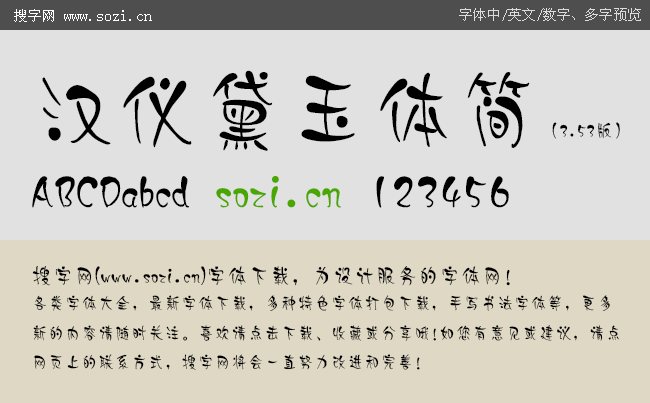
漢儀黛玉簡
搜字網(wǎng)提供一款漢儀黛玉簡中文字體下載,漢儀黛玉字體是一款應(yīng)用于設(shè)計(jì)方面的中文簡體漢字,該字體線條細(xì)膩,字形飄逸大方,整體效果非常出眾,可用于產(chǎn)品設(shè)計(jì)、包裝印刷、報(bào)刊雜志、繪畫創(chuàng)作等廣告設(shè)計(jì)場合使用。